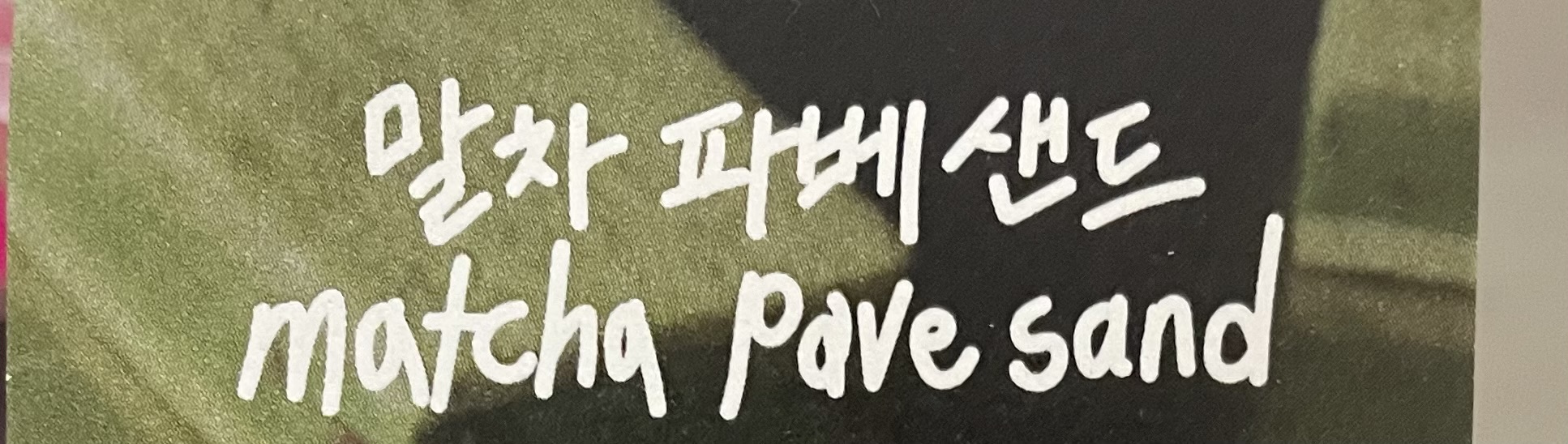
폰트 문의 드려요 sun*** 2023.08.26 ‘말차 파베샌드’ 글씨 폰트 문의 드립니다 댓글 0 등록 모바일 아티스트 폰트가 아닌 손글씨 같습니다. 2023-08-28 답글 달기 댓글 더보기 쉽고 빠르게 가장 비슷한 폰트를 알고 싶다면? 이미지로 검색하기
폰트가 아닌 손글씨 같습니다.